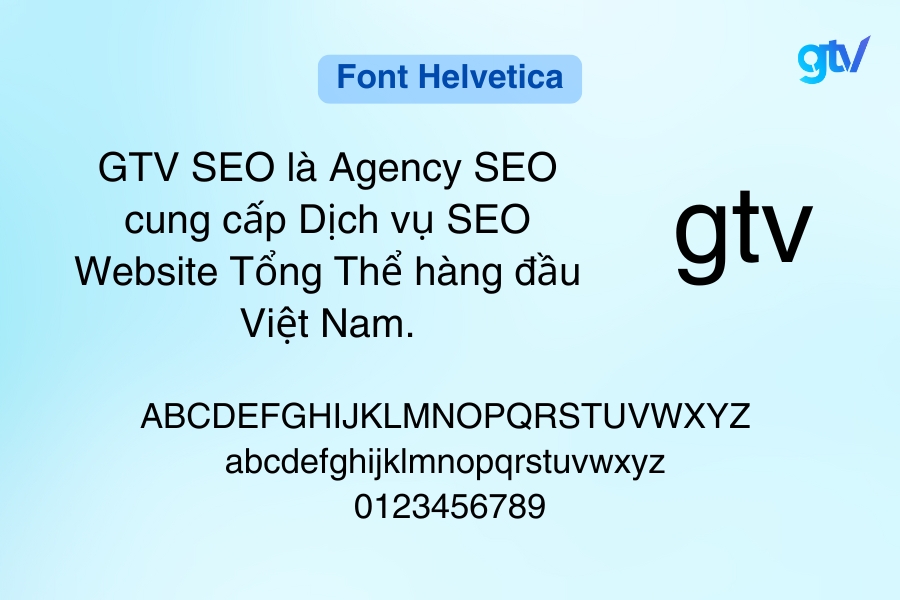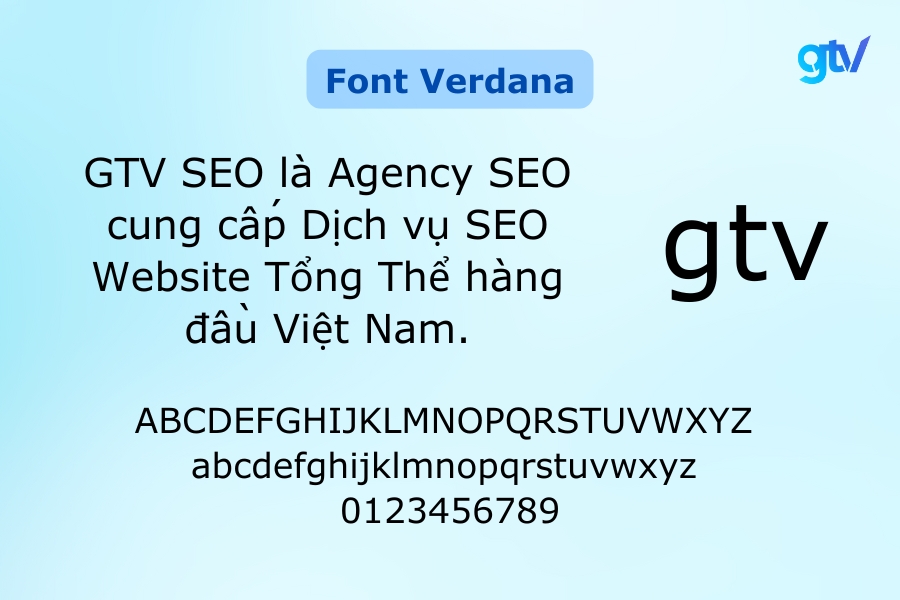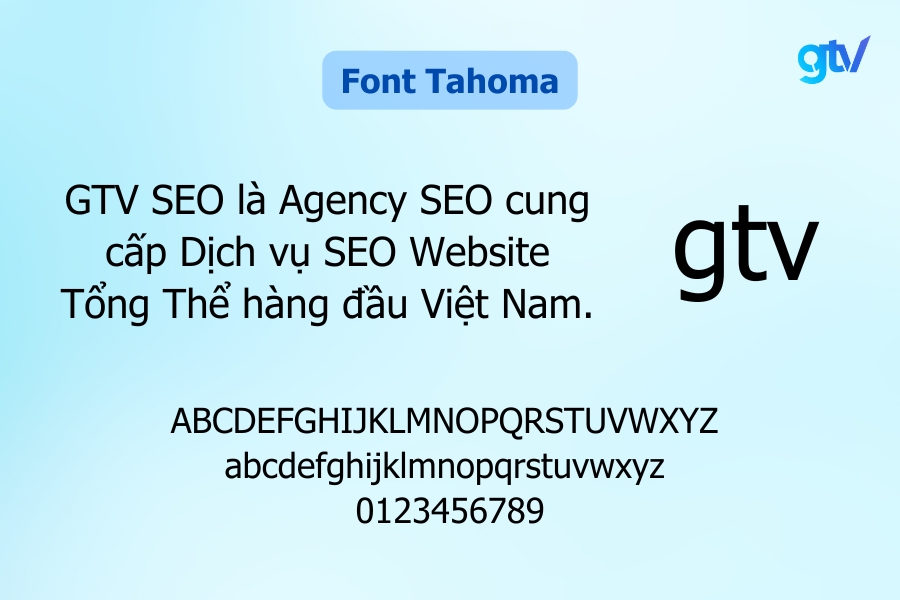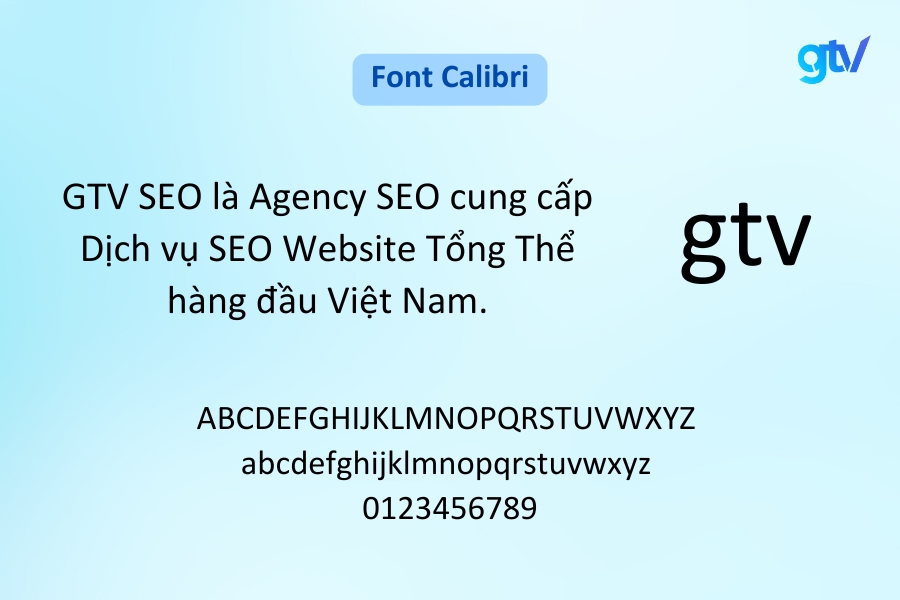
Font chữ đóng vai trò quan trọng trong thiết kế web, tác động trực tiếp đến trải nghiệm người dùng và nhận diện thương hiệu. Đặc biệt, đối với tiếng Việt, việc chọn lựa một font chữ đẹp không chỉ giúp nâng cao tính thẩm mỹ mà còn đảm bảo sự dễ đọc và tính chuyên nghiệp.
Bài viết này sẽ giới thiệu tới bạn hơn 30 font chữ Tiếng Việt đẹp và miễn phí dành riêng cho website, giúp bạn dễ dàng tạo ra một giao diện hấp dẫn và thân thiện với người dùng. Đặc biệt, với các dự án cá nhân hoặc doanh nghiệp nhỏ, việc sử dụng font chữ miễn phí mang lại lợi ích to lớn về mặt chi phí. Bạn có thể dễ dàng tìm thấy những font chữ chất lượng trên các nền tảng uy tín như Google Fonts hay Font Squirrel. Hãy cùng khám phá những lựa chọn tuyệt vời này để làm mới diện mạo website của bạn nhé!
Các loại font chữ phổ biến cho Website
Trong thiết kế web, việc hiểu rõ các loại font chữ khác nhau là rất quan trọng để tạo ra typography hiệu quả. Dưới đây là 4 loại font chữ chính và cách sử dụng chúng:
- Font Serif
- Font Sans Serif
- Font Script (Font chữ viết tay)
- Font Display
Font Serif
Font Serif là loại font chữ có các đường nét nhỏ hoặc nét chấm ở cuối mỗi nét chính của ký tự. Đây là một trong những kiểu chữ cổ điển nhất, gắn liền với các ấn phẩm in ấn truyền thống.
Đặc điểm: Có các nét nhỏ (serif) ở cuối mỗi nét chữ chính.
Công dụng phổ biến:
- Sử dụng nhiều trong in ấn như sách, báo, và tạp chí.
- Phù hợp cho các tài liệu chính thức, học thuật.
- Tạo cảm giác uy tín cho các website tin tức hoặc tổ chức lâu đời.
Ví dụ tiêu biểu: Times New Roman, Georgia, Garamond.
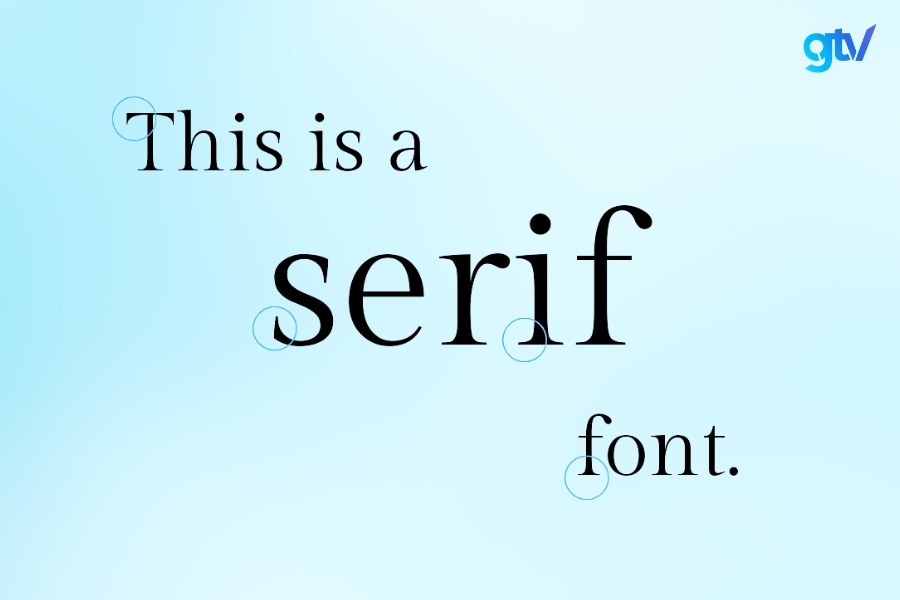
Font Sans Serif
Font Sans Serif là loại font không có các nét nhỏ (serif) ở cuối các nét chính, tạo nên một thiết kế sạch sẽ, hiện đại và đơn giản. Loại font này xuất hiện nhiều trong các thiết kế đương đại và giao diện người dùng kỹ thuật số.
Đặc điểm: Không có các nét nhỏ ở cuối, tạo cảm giác gọn gàng.
Công dụng phổ biến:
- Lý tưởng cho nội dung số, từ desktop đến mobile.
- Thích hợp cho các website hiện đại, ứng dụng di động.
- Dễ đọc trên màn hình với kích thước nhỏ.
Ví dụ tiêu biểu: Arial, Helvetica, Verdana, Roboto.
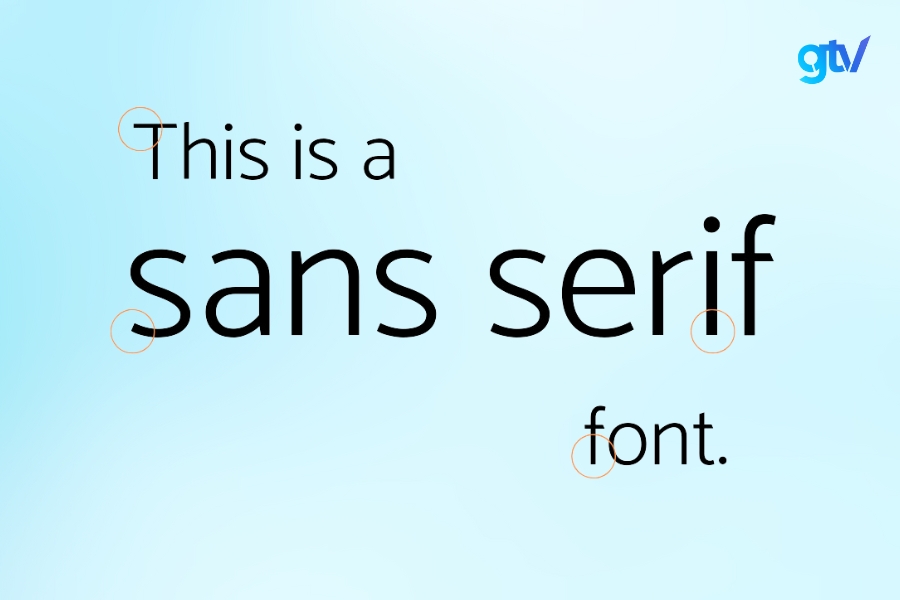
Font Script (Font chữ viết tay)
Font Script được thiết kế để mô phỏng chữ viết tay, mang đến một phong cách cá nhân, mềm mại và nghệ thuật. Font script có thể tạo nên sự gần gũi, thân thiện hoặc thanh lịch tùy thuộc vào thiết kế cụ thể của nó.
Đặc điểm: Giống chữ viết tay, thường có các nét nối liền mạch.
Công dụng phổ biến:
- Thiệp mời, lời chúc.
- Tạo điểm nhấn trong thiết kế.
- Phù hợp cho các website thời trang, nghệ thuật.
Ví dụ tiêu biểu: Pacifico, Dancing Script, Brush Script MT.
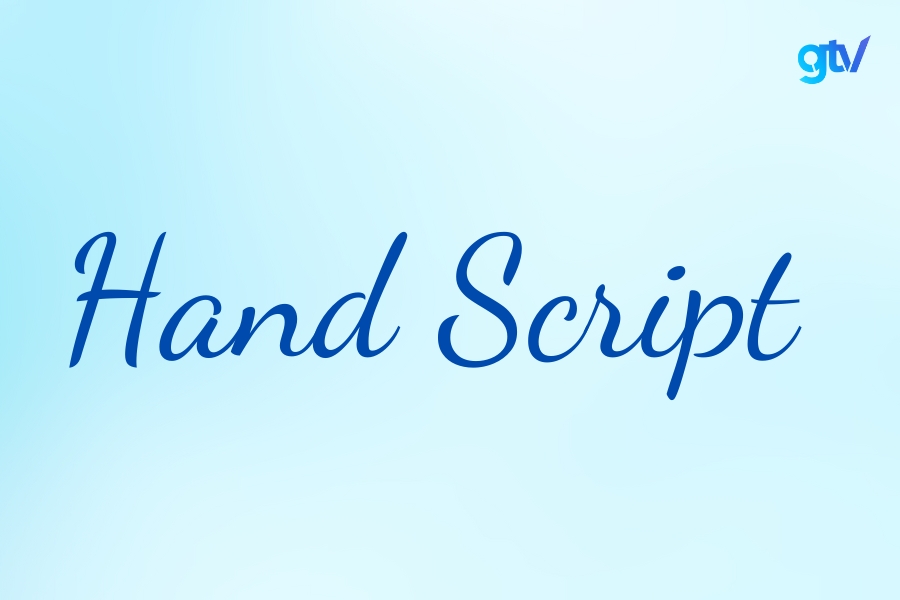
Font Display
Font Display là loại font chữ được thiết kế đặc biệt để sử dụng trong các tiêu đề lớn hoặc logo, nơi cần tạo ấn tượng mạnh mẽ. Font display thường có thiết kế độc đáo và được sử dụng để thu hút sự chú ý ngay lập tức.
Đặc điểm: Thiết kế độc đáo, thường có kích thước lớn.
Công dụng phổ biến:
- Tiêu đề, slogan.
- Logo, thương hiệu.
- Tạo điểm nhấn trong thiết kế.
Ví dụ tiêu biểu: Lobster, Bebas Neue, Impact.
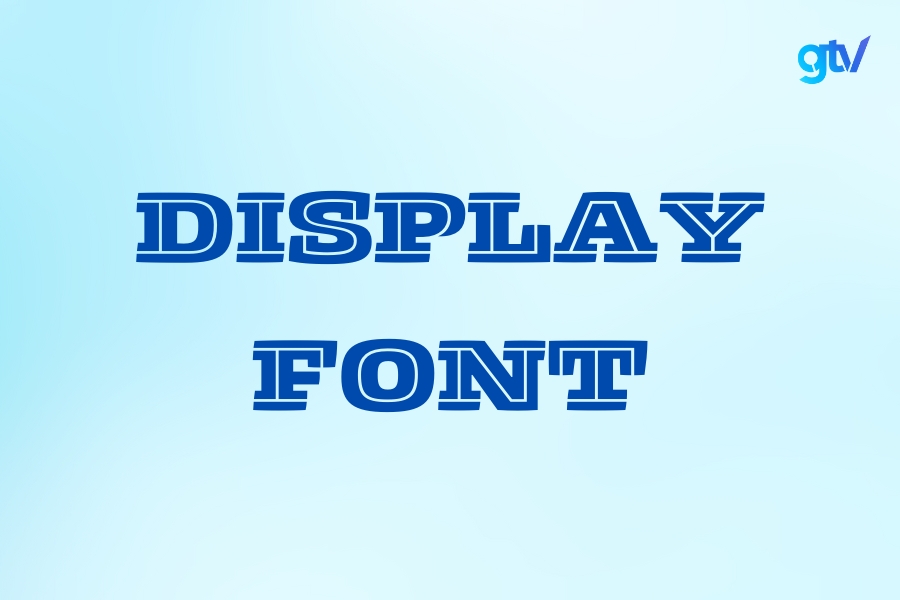
Mỗi loại font chữ đều có ưu điểm riêng và phù hợp với các mục đích sử dụng khác nhau. Khi thiết kế website, việc kết hợp các loại font chữ một cách hợp lý có thể tạo ra sự cân bằng và thu hút trong giao diện. Ví dụ, bạn có thể sử dụng font Display cho tiêu đề chính, font Sans Serif cho nội dung và font Script cho các điểm nhấn đặc biệt. Điều quan trọng là đảm bảo sự hài hòa và dễ đọc trong tổng thể thiết kế của bạn.
Top 30+ font chữ Tiếng Việt miễn phí cho Website
Dưới đây là danh sách 30+ font chữ tiếng Việt miễn phí được yêu thích, hỗ trợ đầy đủ dấu tiếng Việt và dễ dàng tích hợp cho các dự án web của bạn.
1. Source Sans Pro
Source Sans Pro giúp website của bạn trở nên rõ ràng và dễ đọc hơn, phù hợp cho các trang cần nhiều nội dung văn bản.
- Đặc điểm: Đơn giản, rõ ràng và dễ đọc.
- Ứng dụng: Phù hợp cho nội dung chính, đặc biệt với các bài viết dài.
- Ưu điểm: Hỗ trợ tốt trên nhiều kích cỡ khác nhau, cung cấp nhiều độ đậm, dễ dàng tạo điểm nhấn trong thiết kế.
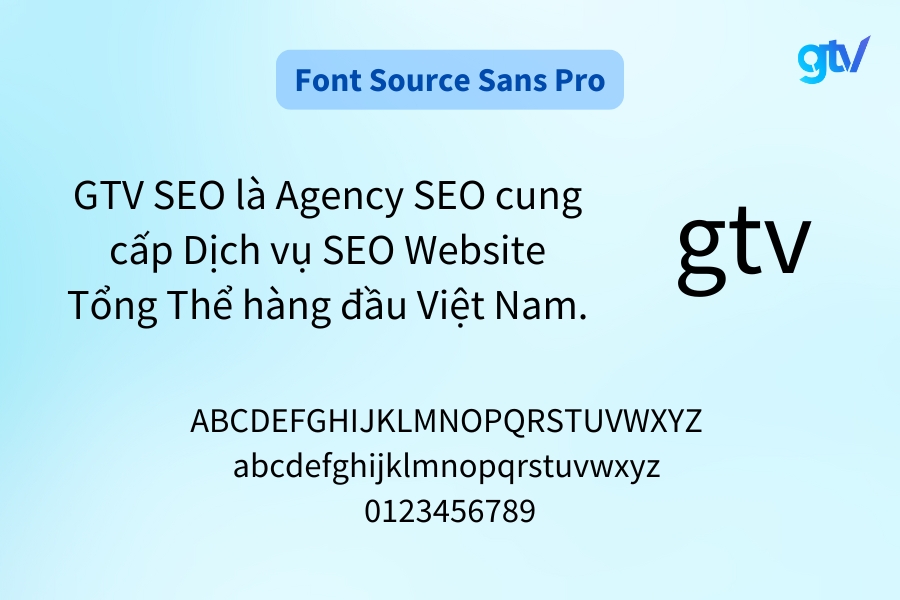
2. Playfair Display
Playfair Display là font chữ mang đến vẻ đẹp cổ điển và thanh lịch cho website. Nó đặc biệt phù hợp cho các tiêu đề trang web nghệ thuật, nội dung quảng cáo sang trọng, và tạo điểm nhấn trong thiết kế.
- Đặc điểm: Cổ điển, thanh lịch.
- Ứng dụng: Lý tưởng cho các tiêu đề hoặc trang web nghệ thuật.
- Ưu điểm: Mang lại vẻ đẹp cao cấp, rất phù hợp cho các thương hiệu muốn thể hiện sự đẳng cấp.
3. Arial
Arial là một font chữ truyền thống và đáng tin cậy, thích hợp cho mọi loại trang web.
- Đặc điểm: Đa năng, dễ đọc.
- Ứng dụng: Phù hợp cho nhiều loại nội dung, từ website công ty đến blog cá nhân.
- Ưu điểm: Tính tương thích cao, hiển thị tốt trên cả desktop và mobile.
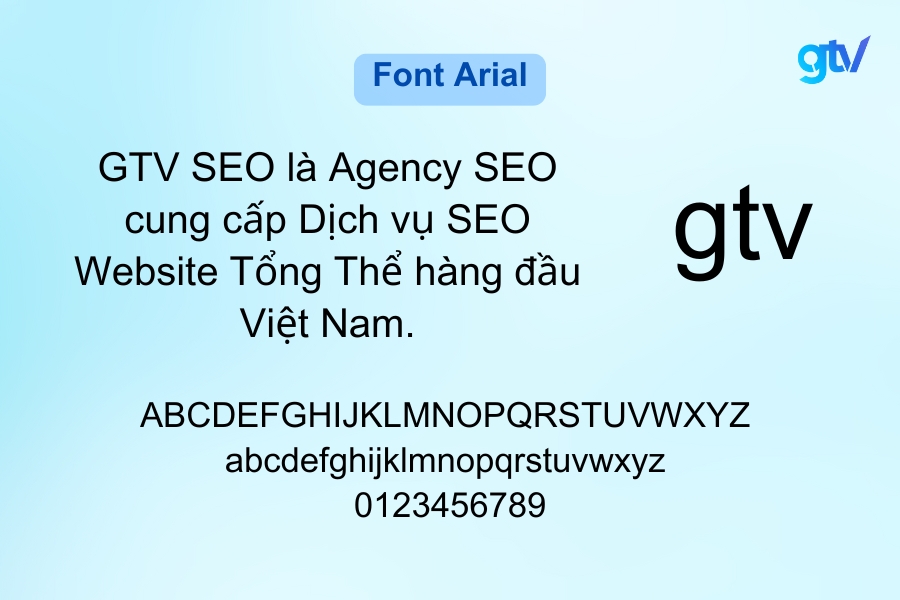
Làm thế nào để kết hợp font chữ hiệu quả trên website?
Để kết hợp font chữ hiệu quả:
- Sử dụng nguyên tắc tương phản: kết hợp font serif với sans-serif.
- Giới hạn số lượng font chữ sử dụng (tối đa 2-3 loại).
- Đảm bảo sự nhất quán trong việc sử dụng font cho các phần tử tương tự.